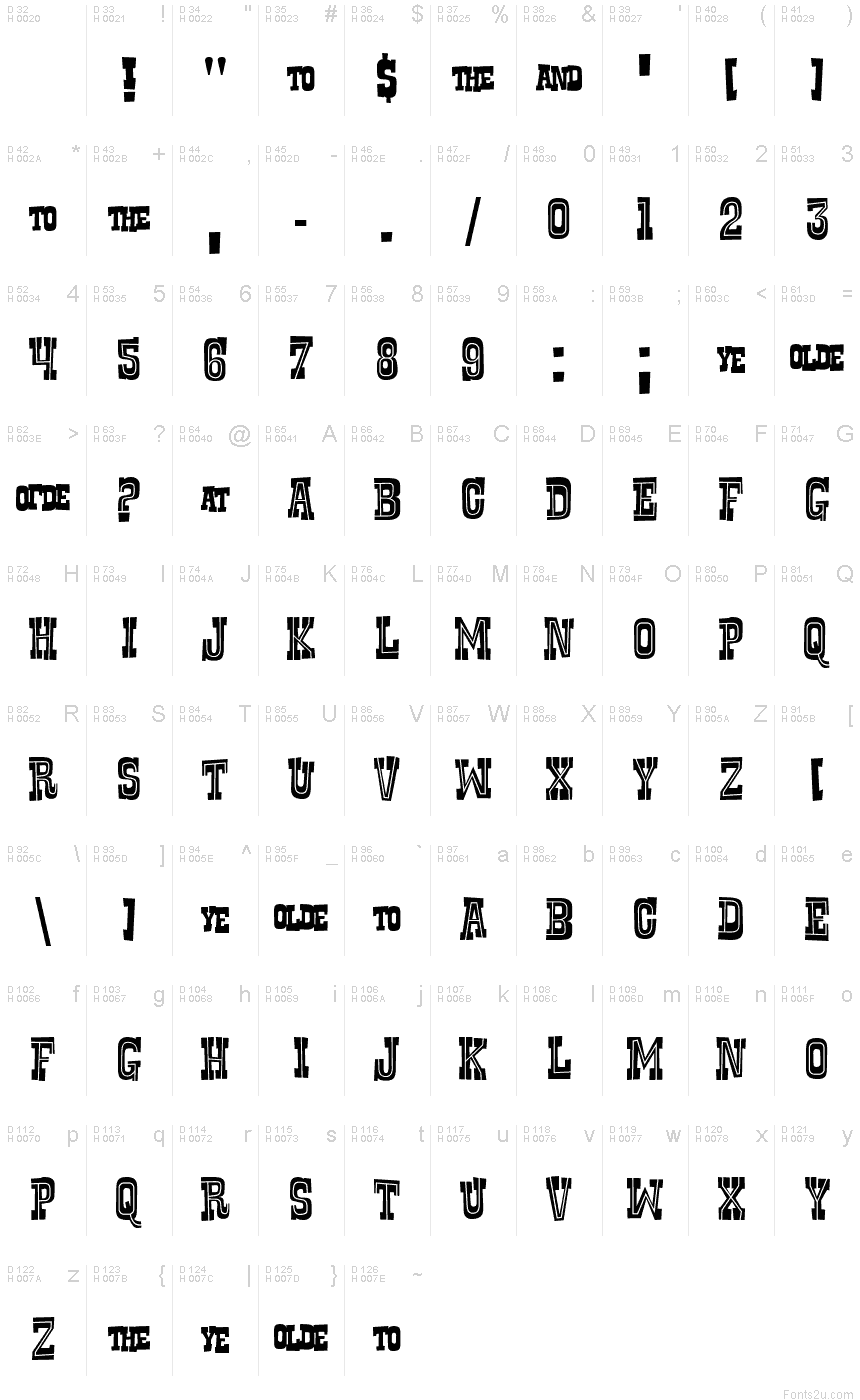
Rustler Fancy od Font"a"licious Fonts to darmowy, westernowy krój pisma w komiksowym stylu, utrzymany w surowym klimacie starych plakatów. Wielkie litery łączą masywne, czarne wypełnienia z przesuniętymi konturami i nierówną wysokością, dzięki czemu całość wygląda jak ręcznie układany napis – głośny i lekko przekrzywiony, co idealnie pasuje do grafiki w stylu komiksowego saloonu.
Najlepiej sprawdza się tam, gdzie nagłówek potrzebuje tego zabawnego, westernowego pazura: na okładkach książek dla dzieci, ulotkach rodeo, zaproszeniach na imprezy, nieszablonowych opakowaniach czy planszach tytułowych. Jako darmowy font, Rustler Fancy świetnie radzi sobie z krótkimi słowami, inicjałami i monogramami, ponieważ zdublowane kontury i skoczne sylwetki znaków błyskawicznie przyciągają wzrok.